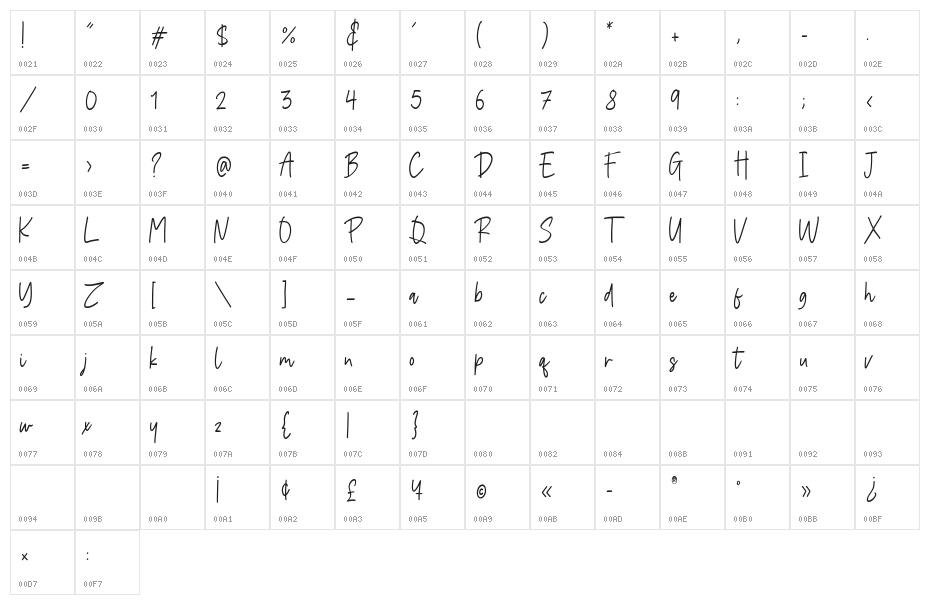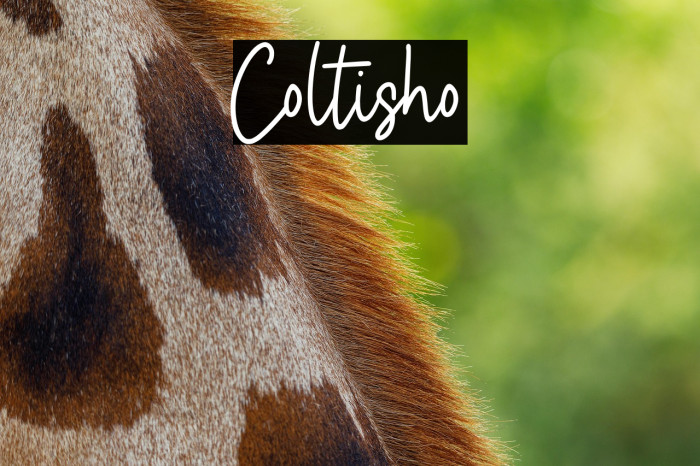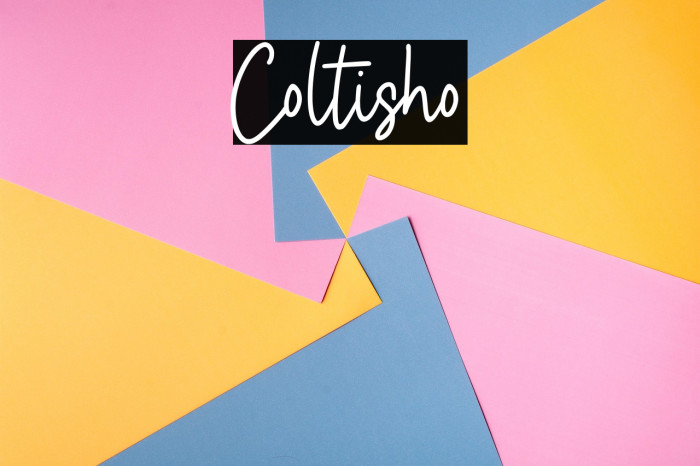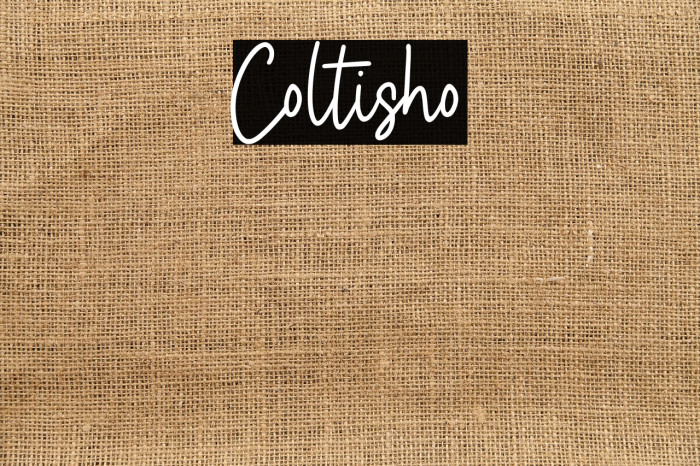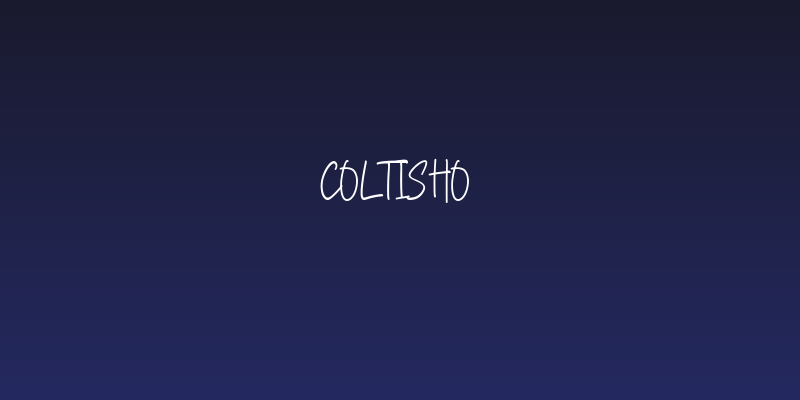
Coltisho Font
| Stile generale | Casual, Playful |
| Caso d'uso | Logos, Headlines, Social media graphics |
| Progetti proposti | Ideal for greeting cards, personal branding, social media graphics, and creative projects that benefit from a personal touch. |